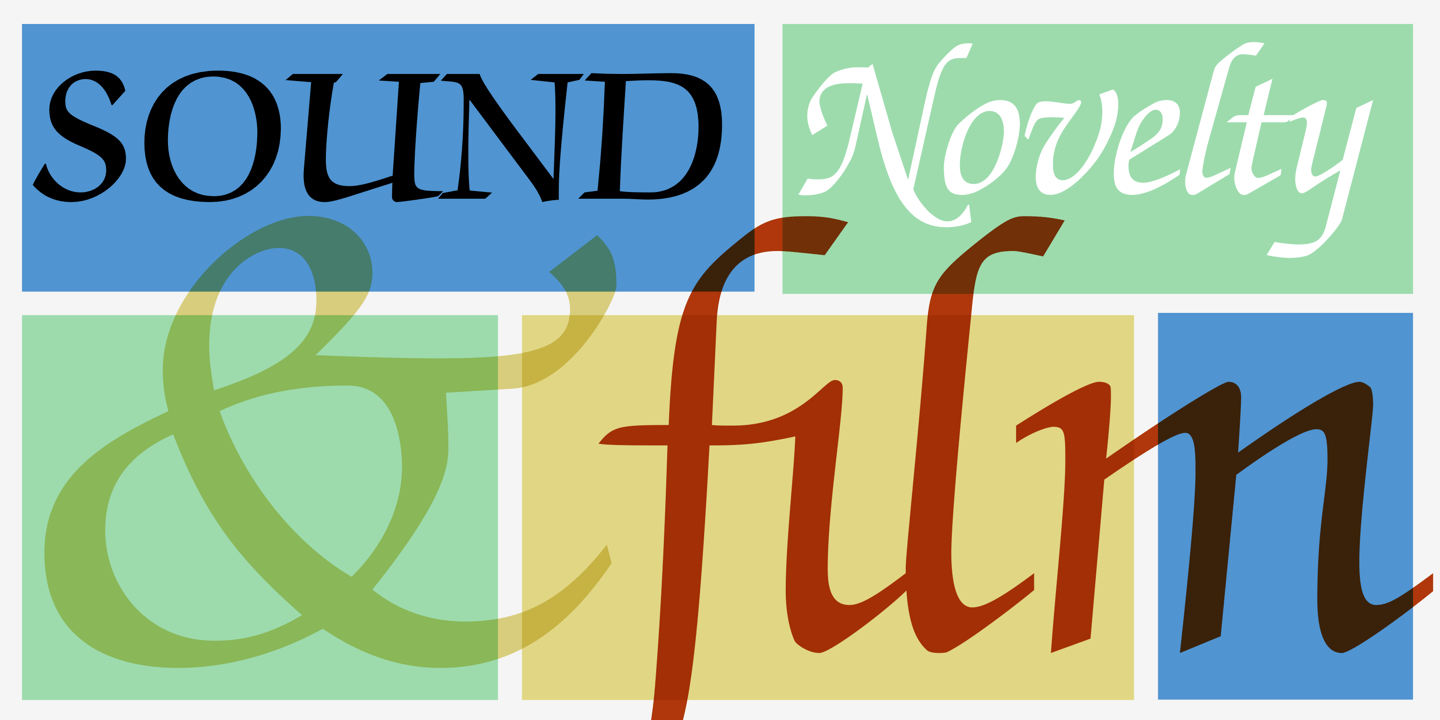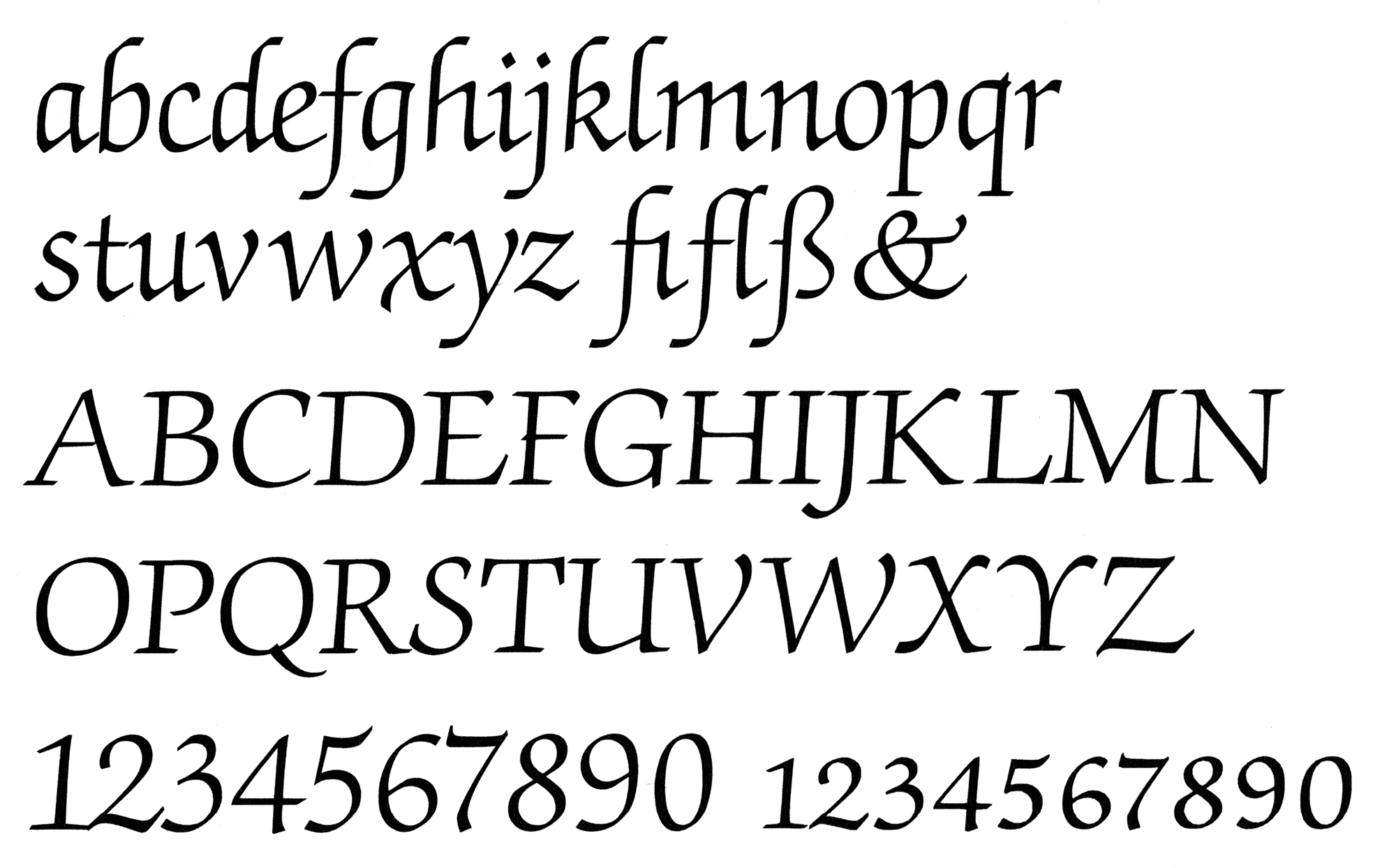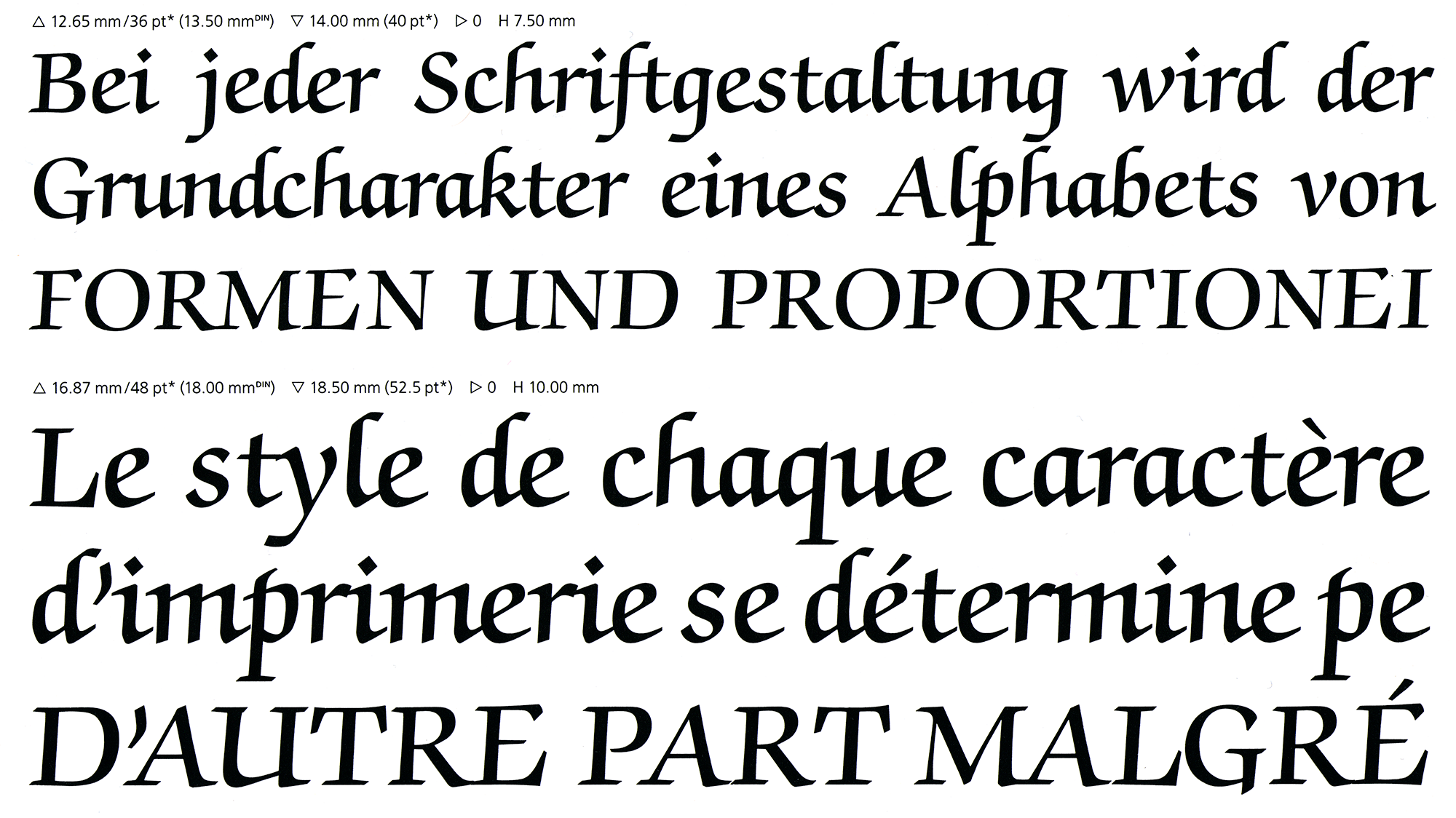
- 1979
- Antiqua Schreibschrift
Die ITC Zapf Chancery von Hermann Zapf ist eine Schriftfamilie mit kalligrafischem Duktus und erschien 1979 über die International Typeface Corporation. Durch die Verwendung als Systemfont im Apple LaserWriter sowie unter Windows und MacOS fand die Schriftfamilie eine große Verbreitung und wurde vielfach verwendet. Zur über ITC erhältlichen Schriftfamilie gehörten vier Strichstärken und zwei kursive Schnitte.
Alle Schnitte sind heute als Pro-Version mit erweiterter lateinischer Belegung, Kapitälchen (in den aufrechten Schnitten) und mehreren Ziffernsets über Monotype verfügbar.